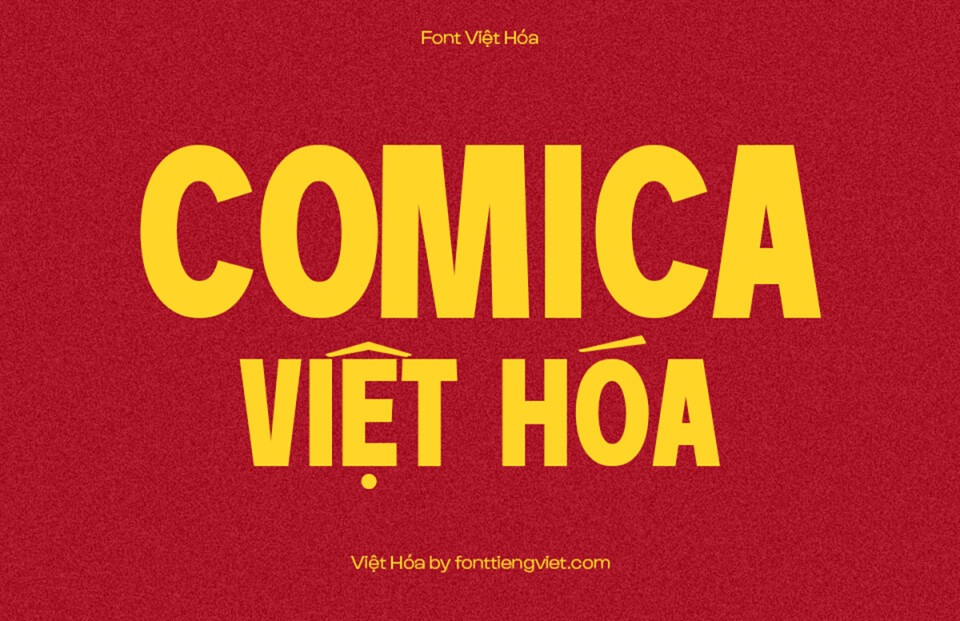
Font Việt hóa 1FTV VIP Comica – Font Không Chân Cổ Điển Cho Thiết Kế Tiêu Đề
Giới thiệu về Font Việt hóa 1FTV VIP Comica – Font Không Chân Cổ Điển Cho Thiết Kế Tiêu Đề
Trong thế giới đồ họa hiện đại, việc lựa chọn một bộ Font Miễn Phí chất lượng luôn là ưu tiên hàng đầu của các nhà thiết kế chuyên nghiệp lẫn người mới bắt đầu. Font Việt hóa 1FTV VIP Comica – Font Không Chân Cổ Điển Cho Thiết Kế Tiêu Đề nổi lên như một giải pháp hoàn hảo, kết hợp giữa sự tinh tế của phong cách cổ điển và tính ứng dụng cao của kiểu chữ không chân (Sans Serif). Bộ font này không chỉ mang lại vẻ ngoài gọn gàng mà còn chứa đựng hơi thở của những ấn phẩm truyện tranh và quảng cáo thập niên cũ, giúp sản phẩm thiết kế trở nên nổi bật và thu hút thị giác ngay từ cái nhìn đầu tiên.
Đặc điểm nổi bật của Font Việt hóa 1FTV VIP Comica – Font Không Chân Cổ Điển Cho Thiết Kế Tiêu Đề
Thiết kế tối giản nhưng đầy sức hút
Được xây dựng dựa trên các đường nét tròn trịa và vững chãi, Font Việt hóa 1FTV VIP Comica – Font Không Chân Cổ Điển Cho Thiết Kế Tiêu Đề loại bỏ các chi tiết thừa thãi, tập trung vào độ dày của nét chữ để tạo sự nhấn mạnh. Đặc điểm này giúp kiểu chữ giữ được độ rõ nét tối đa ngay cả khi sử dụng trong các kích thước lớn hoặc hiển thị trên các màn hình có độ phân giải khác nhau. Cấu trúc chữ cái cân đối tạo ra một nhịp điệu đọc dễ chịu, giúp người xem tiếp nhận thông điệp nhanh chóng mà không bị rối mắt bởi các đường nét cầu kỳ.
Khả năng tương thích tiếng Việt hoàn hảo
Một trong những rào cản lớn nhất khi sử dụng font quốc tế chính là lỗi dấu tiếng Việt. Tuy nhiên, với phiên bản Font Việt hóa 1FTV VIP Comica – Font Không Chân Cổ Điển Cho Thiết Kế Tiêu Đề, mọi vấn đề về hiển thị đã được giải quyết triệt để. Các dấu thanh như huyền, sắc, hỏi, ngã, nặng được tinh chỉnh vị trí một cách tỉ mỉ, đảm bảo không bị dính vào thân chữ hay gây mất thẩm mỹ. Điều này cực kỳ quan trọng đối với các bạn học sinh và giáo viên khi cần thiết kế slide bài giảng hoặc báo tường sinh động mà vẫn giữ được sự chuyên nghiệp.
Ứng dụng thực tế của Font Việt hóa 1FTV VIP Comica
Thiết kế tiêu đề và banner quảng cáo
Đúng như tên gọi, thế mạnh lớn nhất của bộ font này là dành cho tiêu đề. Với trọng lượng chữ lớn, nó rất phù hợp để làm headline cho các bìa sách, poster phim, hoặc banner truyền thông trên mạng xã hội. Khi kết hợp cùng những gam màu tương phản cao, font chữ sẽ tạo nên một hiệu ứng thị giác mạnh mẽ, giúp định vị thương hiệu hiệu quả.
Sáng tạo nội dung cho môi trường giáo dục
Trong môi trường học đường, việc sử dụng các font chữ quá cứng nhắc đôi khi làm giảm đi sự sáng tạo. Font Việt hóa 1FTV VIP Comica – Font Không Chân Cổ Điển Cho Thiết Kế Tiêu Đề mang đến sự gần gũi, vui nhộn nhưng vẫn đủ nghiêm túc. Thầy cô có thể dùng font này để làm tiêu đề bài học, giúp các em học sinh cảm thấy hứng thú hơn với kiến thức được truyền tải qua những hình ảnh trình chiếu đẹp mắt.
Kết luận và trải nghiệm người dùng
Việc sở hữu một bộ chữ đẹp và đầy đủ dấu tiếng Việt sẽ giúp bạn tiết kiệm rất nhiều thời gian trong quá trình sáng tạo. Nếu bạn đang tìm kiếm một công cụ hỗ trợ đắc lực cho các dự án thiết kế mang phong cách retro hoặc cần sự rõ ràng tuyệt đối, đừng bỏ qua Font Miễn Phí, Font Việt Hóa, Font Việt hóa 1FTV VIP Comica – Font Không Chân Cổ Điển Cho Thiết Kế Tiêu Đề. Đây chắc chắn là mảnh ghép còn thiếu để nâng tầm các tác phẩm đồ họa của bạn lên một đẳng cấp mới. Hãy thử nghiệm ngay hôm nay để thấy được sự khác biệt mà bộ font độc đáo này mang lại cho tiêu đề của bạn.